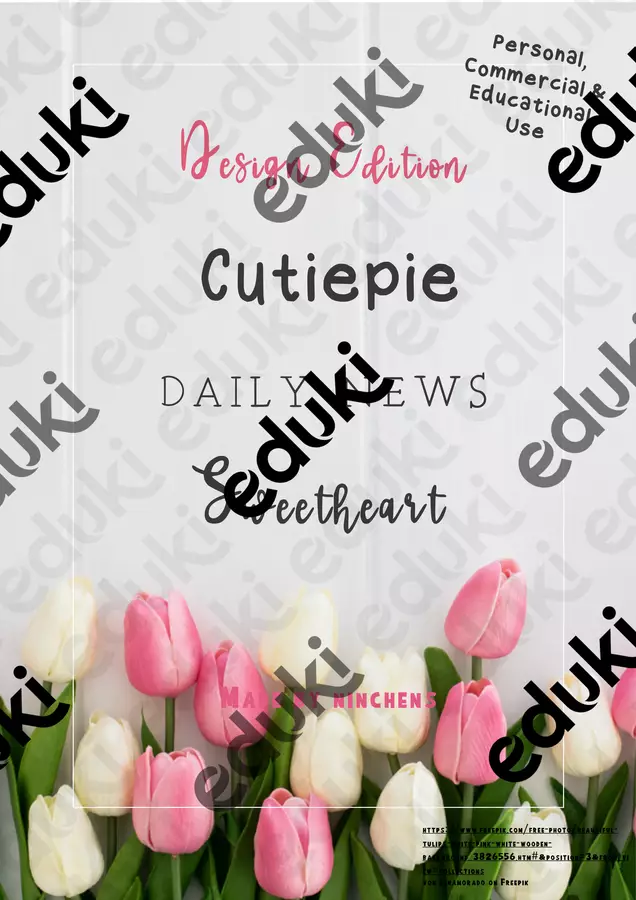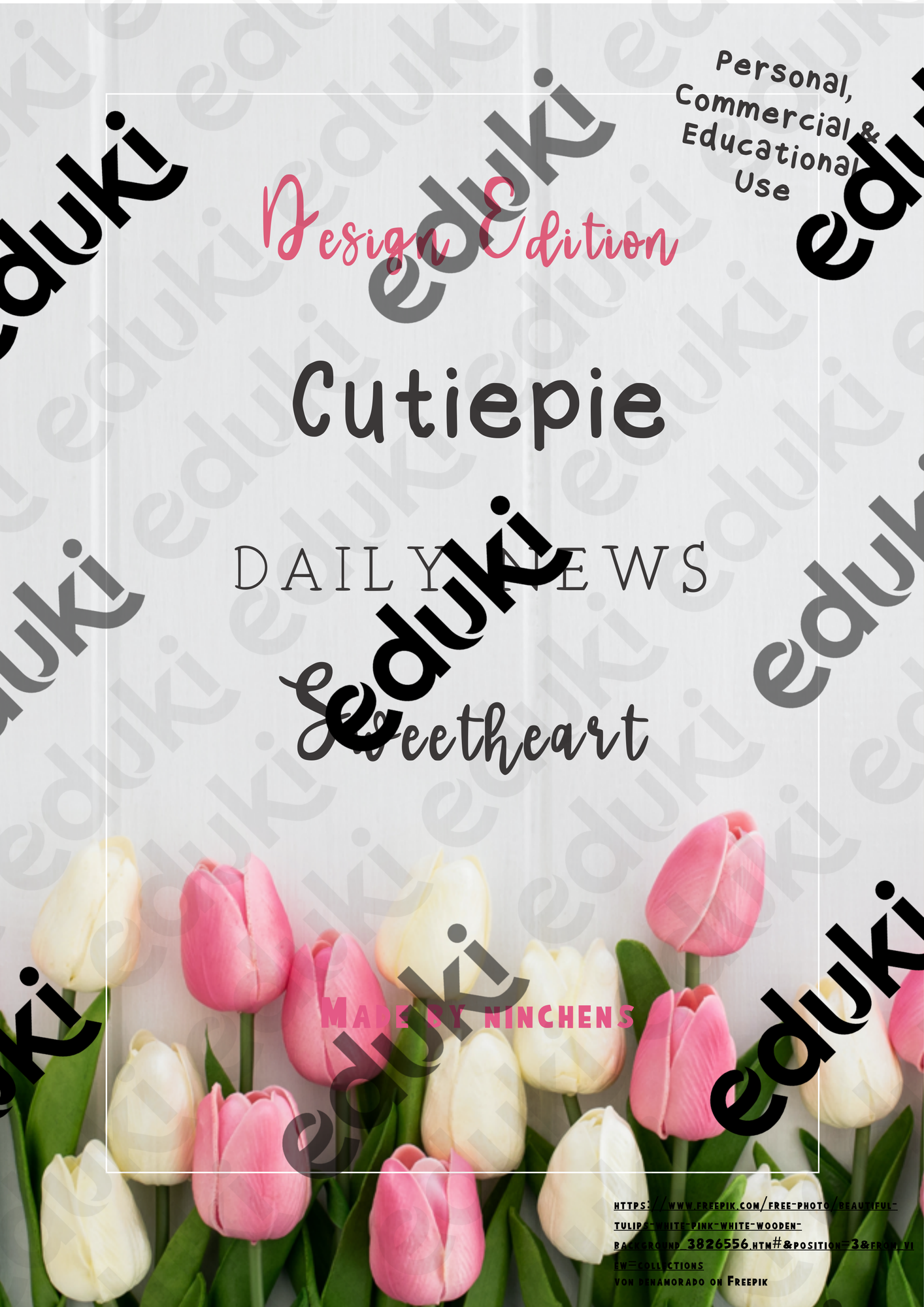
Vorschau - selbst erstellte Schriftarten - Schriftarten-Set: Design Edition - Deckblatt
selbst erstellte Schriftarten - Schriftarten-Set: Design Edition - ninchenscreativelife - Deckblatt
Das Schriftarten-Set Design Edition ist umfasst drei Fonts, mit denen besondern schöne, ästhetische Designs und Vorlagen kreiert werden können. Das Set enthält die Schriftarten cutiepie, daily news & sweetheart
Schriftarten-Set: Design Edition